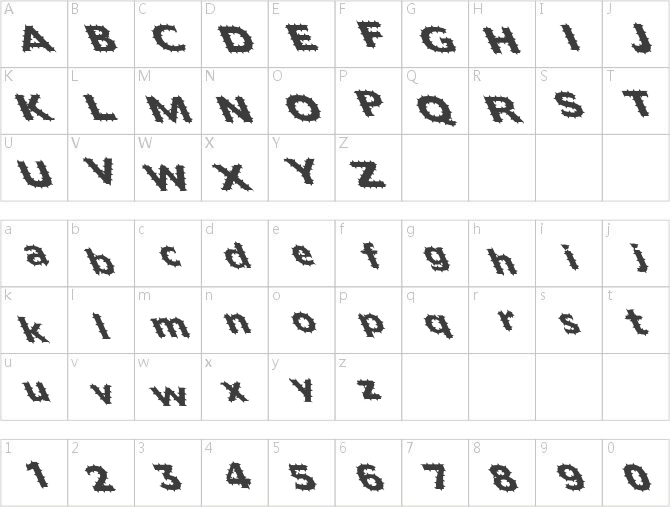
FZ BASIC 55 SPIKED LEFTY
FZ BASIC 55 SPIKED LEFTY介紹
FZ BASIC 55 SPIKED LEFTY字體字庫是一款讓人賞心悅目、百看不厭的英文字體,適合各類廣告和產品包裝設計應用,字體大小0.08MB,格式為ttf字體,上傳用戶是惠祥博達,作者/版權方為未知